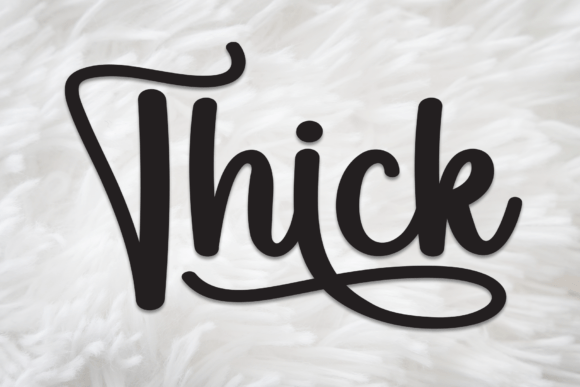
Thick
Ulasan Lengkap Font "Thick" – Desain Menyala dengan Sentuhan Manis
Jika Anda mencari font yang memadukan kehangatan dan keunikan, "Thick" adalah pilihan yang tepat. Terinspirasi oleh gaya tulisan tangan, font ini menampilkan karakter tebal dan elegan, namun tetap mempertahankan nuansa bersahabat dan ceria.
Portrays yang Memukau dalam Setiap Bidang
- Undangan Pernikahan – Tambahkan sentuhan klasik yang lembut dan hangat pada undangan pernikahan Anda.
- Kartu Ucapan – Sangat cocok untuk kartu ucapan ulang tahun, perayaan, atau terima kasih.
- Desain Grafis Sehari-hari – Ideal untuk brosur, poster, atau presentasi yang membutuhkan keunikan dan kepribadian.
- Konten Digital – Cocok untuk headline, caption media sosial, dan materi pemasaran online.
Keistimewaan font ini terletak pada kemampuan untuk meningkatkan kebahagiaan skema visual tanpa mengorbankan profesionalisme. Dengan garis tebal yang mudah dibaca, "Thick" memastikan pesan Anda tampak jelas dan menyenangkan.
Kesimpulan
Mulailah berkreasi dengan "Thick" dan rasakan perbedaan dalam setiap proyek Anda. Font yang bersahabat, manis, dan penuh kebahagiaan – sempurna untuk menambahkan sentuhan whimsical pada desain Anda.